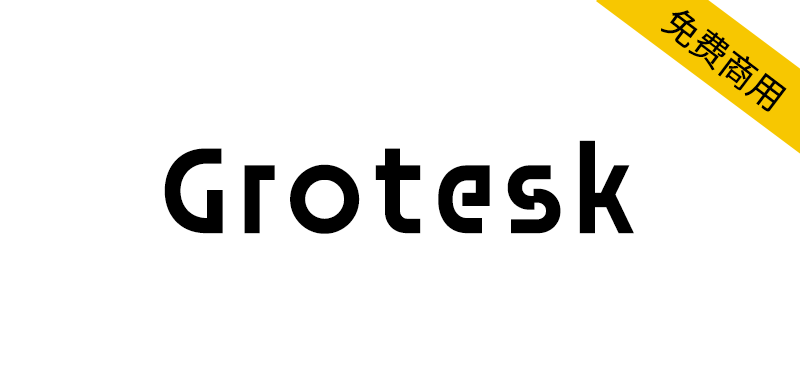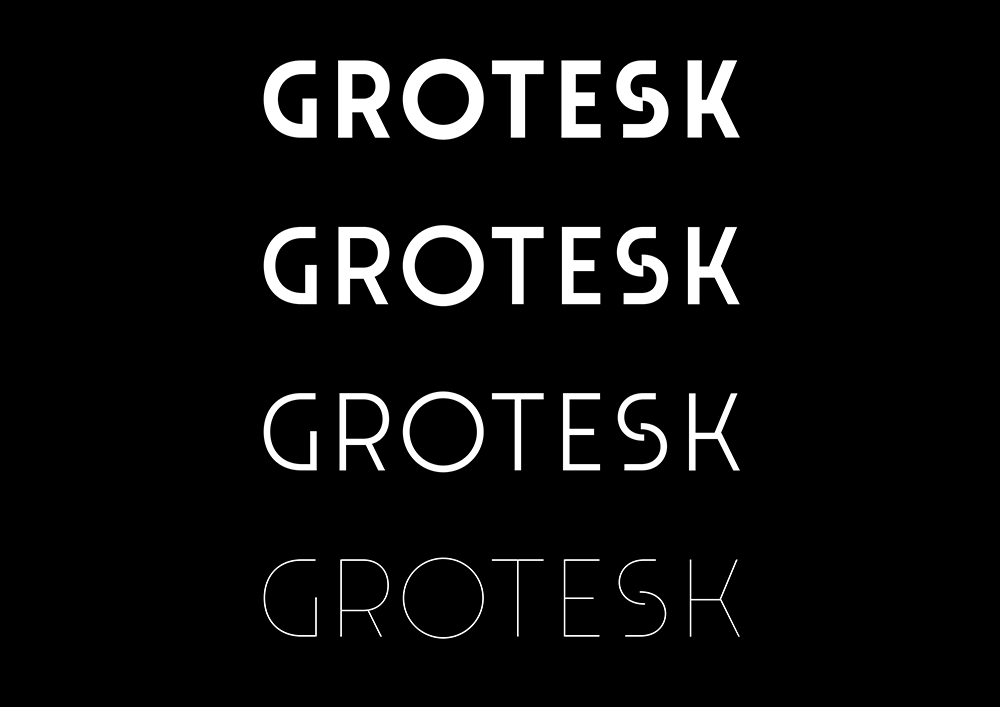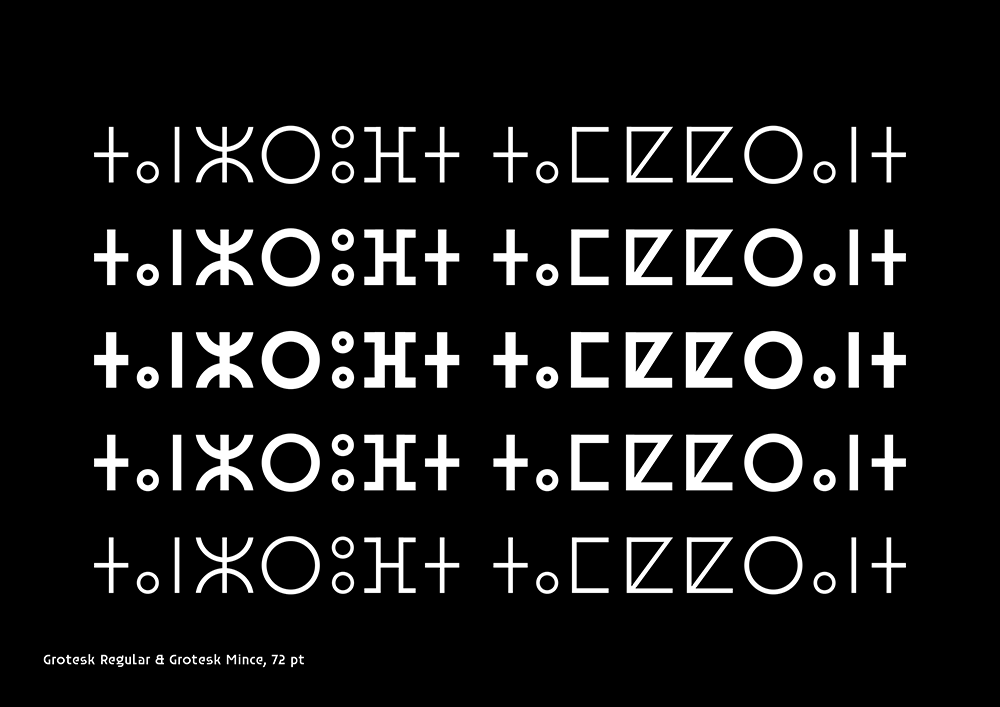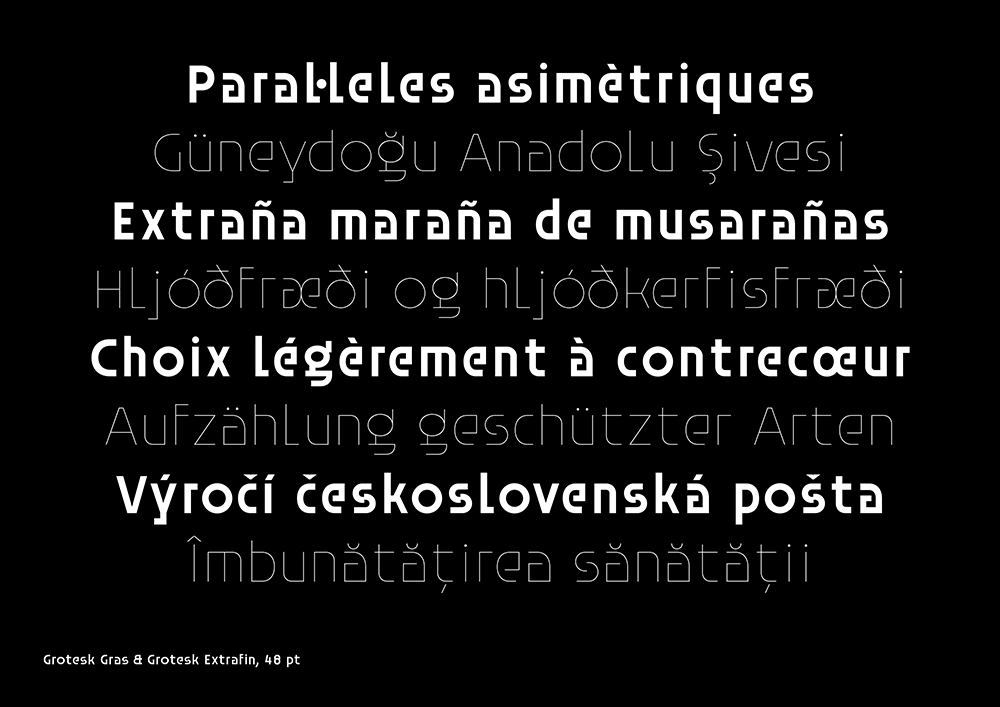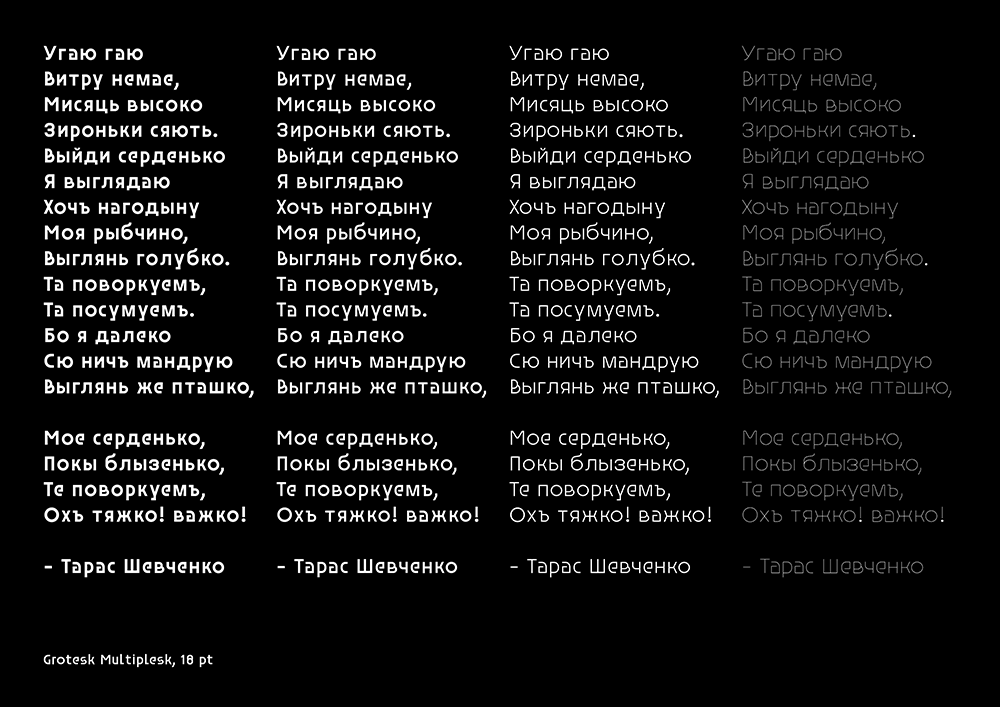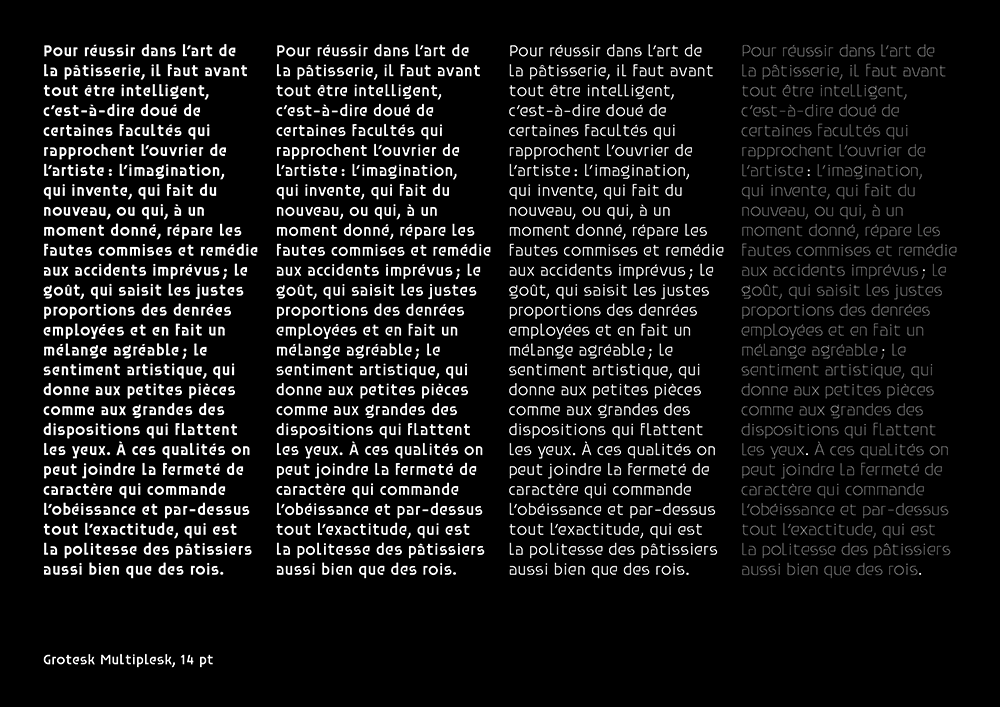
Grotesk是Velvetyne最早出版的字体之一。Grotesk由Frank Adebiaye于2010年设计,并于2012年在Velvetyne上发布,是一种具有非常大间距的几何无衬线字体。Grotesk的原始版本是众所周知的,因为它在巴黎市的官方网站上使用了多年。即使自那以后这座城市的视觉形象发生了变化,Grotesk破碎的“s”仍然可以在这座城市中的一些技术车辆中看到。
2023年,Ariel Martín Pérez开发的Grotesk新版本发布。这个新版本引入了多个的新字重,这意味着您可以在不改变段落宽度的情况下更改字体的粗细。这个新版本还提供了一些微妙的光学校正。最后但并非最不重要的一点是,它通过全新的小写字母集以及对俄语、乌克兰语、Tifinagh和许多基于拉丁语的语言的语言支持,大大扩展了字体的字符集。您可以使用Grotesk为您的文本增添轻松优雅的触感,其微妙的艺术气息将启发任何作品。
Grotesk is one of Velvetyne's first published typefaces. Designed by Frank Adebiaye in 2010 and released on Velvetyne in 2012, Grotesk is a heavily geometric sans serif typeface with an unusually large spacing. The original version of Grotesk is known because it was used on the official website of the city of Paris for many years. Even if the city's visual identity has changed since then, the broken "S" of Grotesk can still be seen in some of the technical vehicles of the city.
In 2023, a new version of Grotesk developed by Ariel Martín Pérez was released. This new version introduces new weights that are multiplexed, which means that you can change the weight of the font without changing the width of the paragraphs. This new version also presents some subtle optical corrections. Last but not least, it considerably expands the glyphset of the font with a brand new lowercase set as well as language support for Russian, Ukrainian, Tifinagh and many Latin-based languages.You can use Grotesk to give a relaxed and elegant touch to your texts, its subtle art-déco flavour will enlighten any composition.